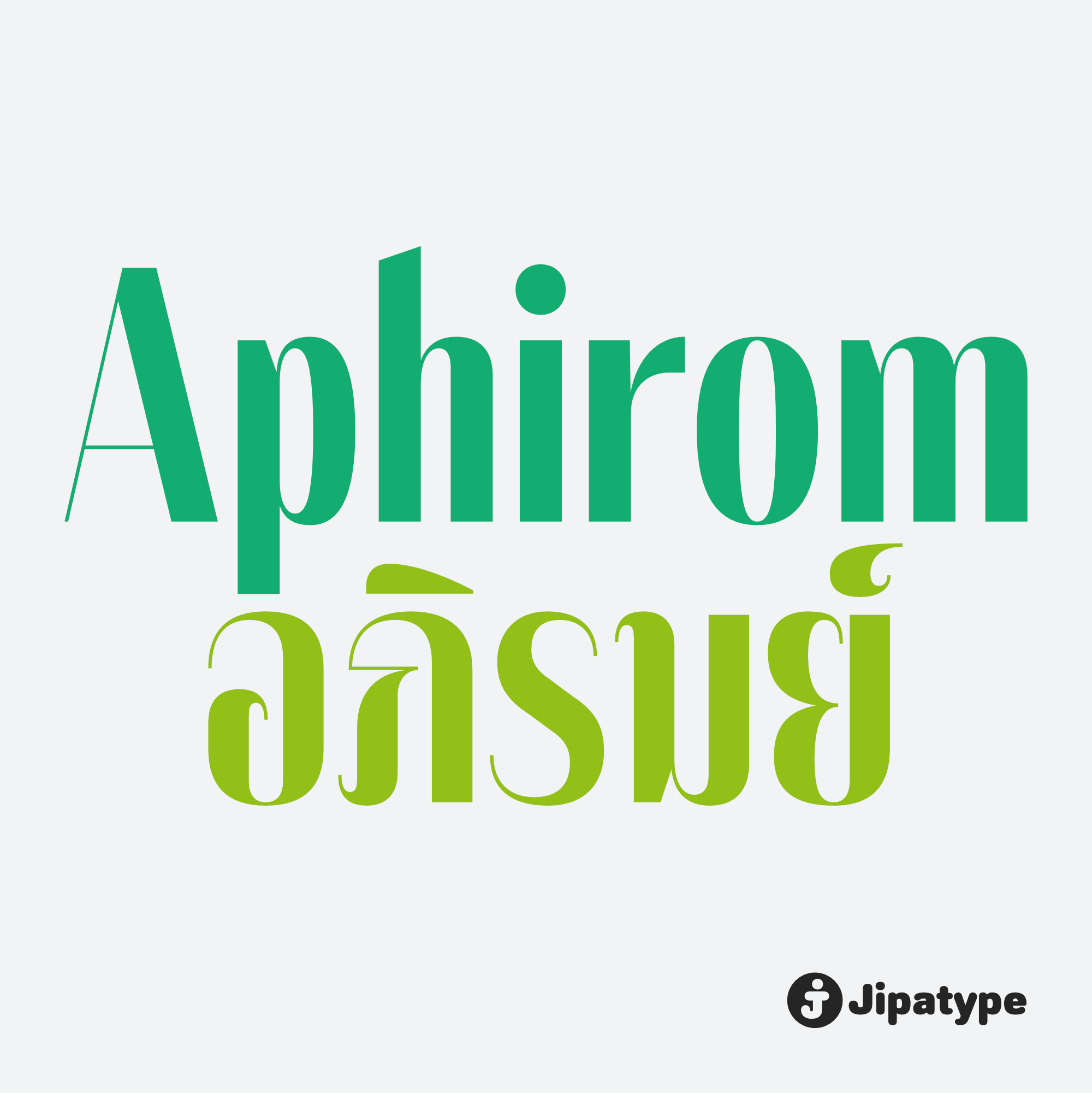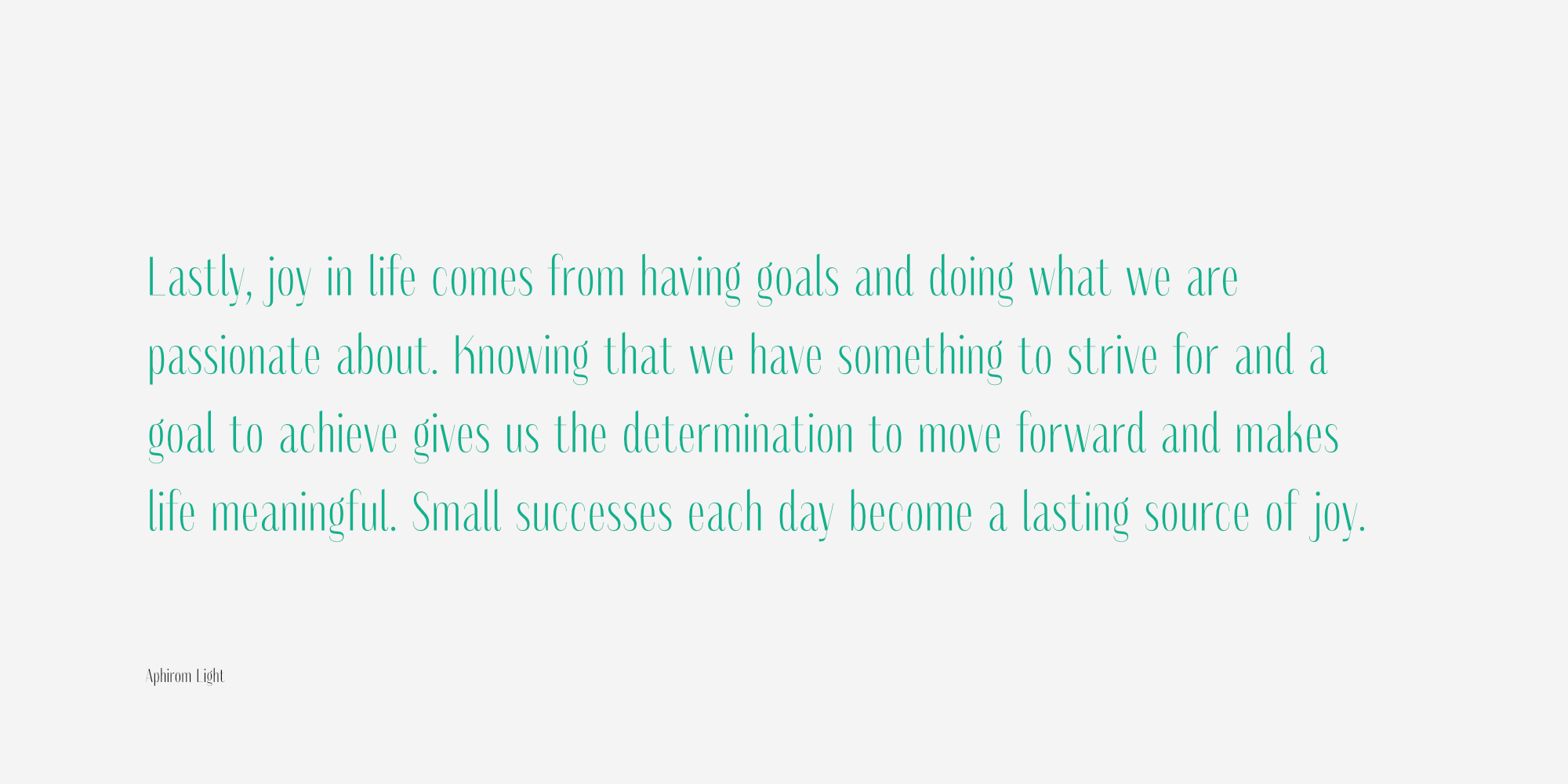
อภิรมย์ | Aphirom
ชื่อฟอนต์ : อภิรมย์ | Aphirom
อภิรมย์ เป็นแบบอักษรคอนทราสต์แซนเซอริฟ มีโครงสร้างตัวอักษรที่แคบ มีเส้นแนวตั้งและแนวนอนเปรียบต่างกัน ให้ความรู้สึกผอมเพรียวและสวยงามเห็นแล้วรู้สึกได้ถึงความอภิรมย์ เหมาะสำหรับสื่อประชาสัมพันธ์ที่ต้องการสื่อสารเรื่องความงาม ความสุขสงบ ธรรมชาติ แบบอักษรนี้ประกอบด้วย 18 รูปแบบ ครอบคลุมน้ำหนักเส้นตั้งแต่บางที่สุดจนถึงหนาที่สุด โดยรองรับทั้งชุดอักษรลาติน 1 และอักษรไทย